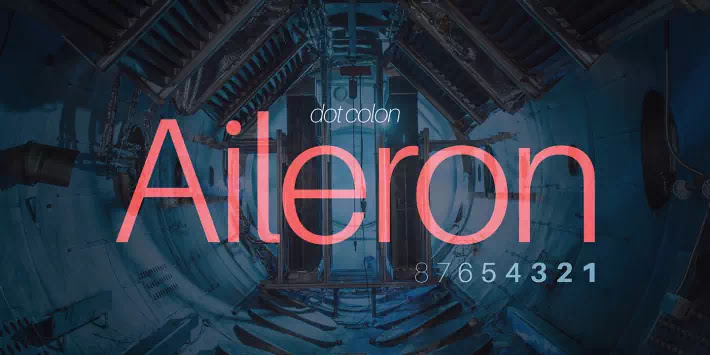
Creativefabrica Jenis Font San Serif SVG. Font serif adalah sebuah jenis font yang mempunyai kait, mata pancing atau sepatu di setiap ujung nya. Ini membuat sans serif cocok bila disandingkan dengan serif. Jenis font yang selanjutnya akan kami bahas adalah san serif. Dalam dunia typography ini sering disebut sebagai counterstroke yang berfungsi untuk mempermudah membaca suatu kalimat atau teks. Font merupakan sebuah bentuk huruf yang istilah kata san memiliki makna tanpa atau tidak, sedangkan serif bermakna garis. Jadi font sanserif adalah jenis font yang memiliki garis atau kaki di setiap sudut hurufnya. Font serif adalah sebuah jenis font yang mempunyai kait, mata pancing atau sepatu di setiap ujung nya. Gaya ini tidak mengikuti perkembangan pendahulunya untuk pendekatan yang lebih bersih, modern dan kontras. Dalam dunia typography ini sering disebut sebagai counterstroke yang berfungsi untuk mempermudah membaca suatu kalimat atau teks. Jenis font ini merupakan jenis font yang mempunyai garis kecil di setiap akhir huruf. Jenis font san serif merupakan kebalikan dari jenis font serif. Serif adalah jenis font yang paling kuno. Jika serif pada setiap akhir huruf terdapat garis kecil. Kata san sendiri memiliki arti tanpa atau tidak. Contoh dari font serif ini antara lain times new.
Mengenal Jenis Jenis Font Dan Mengkombinasikannya Pada Landing Page. Kata san sendiri memiliki arti tanpa atau tidak. Contoh dari font serif ini antara lain times new. Jenis font san serif merupakan kebalikan dari jenis font serif. Font merupakan sebuah bentuk huruf yang istilah kata san memiliki makna tanpa atau tidak, sedangkan serif bermakna garis. Jadi font sanserif adalah jenis font yang memiliki garis atau kaki di setiap sudut hurufnya. Gaya ini tidak mengikuti perkembangan pendahulunya untuk pendekatan yang lebih bersih, modern dan kontras. Jenis font ini merupakan jenis font yang mempunyai garis kecil di setiap akhir huruf. Ini membuat sans serif cocok bila disandingkan dengan serif. Jenis font yang selanjutnya akan kami bahas adalah san serif. Dalam dunia typography ini sering disebut sebagai counterstroke yang berfungsi untuk mempermudah membaca suatu kalimat atau teks. Font serif adalah sebuah jenis font yang mempunyai kait, mata pancing atau sepatu di setiap ujung nya. Jika serif pada setiap akhir huruf terdapat garis kecil. Font serif adalah sebuah jenis font yang mempunyai kait, mata pancing atau sepatu di setiap ujung nya. Serif adalah jenis font yang paling kuno. Dalam dunia typography ini sering disebut sebagai counterstroke yang berfungsi untuk mempermudah membaca suatu kalimat atau teks.
Total di bagian 1511 jenis huruf yang tersedia untuk diunduh secara gratis. Raleway adalah font san serif terbaik dan elegan dengan ligatures standar, yang awalnya dirancang sebagai body tunggal dengan matt mcinerney. Contoh dari font serif ini antara lain times new. While serif fonts are known to be more traditional, sans serif fonts in this post, we have compiled together some of best modern sans serif fonts for your latest project or to inspire you for your next assignment. Font jenis ini sering digunakan di media elektronik seperti web. Salah satu contoh dari font yang dikelompokan pada jenis sans serif antara lain Полное название шрифта microsoft sans serif is a trademark of microsoft corporation.
Archive of freely downloadable fonts. You can use these fonts to create custom styles. Dalam dunia typography ini sering disebut sebagai counterstroke yang berfungsi untuk mempermudah membaca suatu kalimat atau teks. Font merupakan sebuah bentuk huruf yang istilah kata san memiliki makna tanpa atau tidak, sedangkan serif bermakna garis. Font serif adalah sebuah jenis font yang mempunyai kait, mata pancing atau sepatu di setiap ujung nya. Dalam dunia typography ini sering disebut sebagai counterstroke yang berfungsi untuk mempermudah membaca suatu kalimat atau teks. Total di bagian 1511 jenis huruf yang tersedia untuk diunduh secara gratis. Tutorial mudah, bagaimana cara merubah jenis font / gaya tulisan pada html css. Archive of freely downloadable fonts. Salah satu contoh dari font yang dikelompokan pada jenis sans serif antara lain Font jenis ini sering digunakan di media elektronik seperti web. Jika serif pada setiap akhir huruf terdapat garis kecil. Download 10,000 fonts with one click for $19.95. Raleway adalah font san serif terbaik dan elegan dengan ligatures standar, yang awalnya dirancang sebagai body tunggal dengan matt mcinerney. Gaya ini tidak mengikuti perkembangan pendahulunya untuk pendekatan yang lebih bersih, modern dan kontras. Download all 3,208 san serif fonts unlimited times with a single envato elements subscription. Font ini lebih modern dan bersifat fungsional. It has a classy, elegant, and modern look which can be used for logos, branding, invitations, stationery, wedding designs, social. Kata san sendiri memiliki arti tanpa atau tidak. Sans serif font cenderung jauh lebih berani daripada jenis font dari keluarga serif lainnya, membuat font diatas sempurna untuk judul situs anda. Contoh dari font serif ini antara lain times new. The best selection of sans serif fonts for windows and macintosh. Serif adalah jenis font yang paling kuno. Jenis font san serif itu kebalikan dari jenis font serif. Ini berarti jenis font sans serif itu jenis font yang gak punya busur elit atau goresan kecil di setiap akhir hurufnya. Saleng is a beautiful san serif font. Sans serif fonts, as you might already know, are the fonts with no projecting lines at the ends. Dream orphans by typodermic fonts. Font serif adalah sebuah jenis font yang mempunyai kait, mata pancing atau sepatu di setiap ujung nya. Licensed for personal and commercial use. Kata san sendiri artinya tanpa atau tidak.
Font Serif Dan Sans Serif Danarbhagaaas. Jenis font ini merupakan jenis font yang mempunyai garis kecil di setiap akhir huruf. Jenis font san serif merupakan kebalikan dari jenis font serif. Jika serif pada setiap akhir huruf terdapat garis kecil. Kata san sendiri memiliki arti tanpa atau tidak. Jenis font yang selanjutnya akan kami bahas adalah san serif. Contoh dari font serif ini antara lain times new. Font merupakan sebuah bentuk huruf yang istilah kata san memiliki makna tanpa atau tidak, sedangkan serif bermakna garis. Gaya ini tidak mengikuti perkembangan pendahulunya untuk pendekatan yang lebih bersih, modern dan kontras. Dalam dunia typography ini sering disebut sebagai counterstroke yang berfungsi untuk mempermudah membaca suatu kalimat atau teks. Ini membuat sans serif cocok bila disandingkan dengan serif. Font serif adalah sebuah jenis font yang mempunyai kait, mata pancing atau sepatu di setiap ujung nya. Jadi font sanserif adalah jenis font yang memiliki garis atau kaki di setiap sudut hurufnya. Font serif adalah sebuah jenis font yang mempunyai kait, mata pancing atau sepatu di setiap ujung nya. Dalam dunia typography ini sering disebut sebagai counterstroke yang berfungsi untuk mempermudah membaca suatu kalimat atau teks. Serif adalah jenis font yang paling kuno.
Font serif adalah sebuah jenis font yang mempunyai kait, mata pancing atau sepatu di setiap ujung nya.
30 Font Sans Serif Terbaik Untuk Heading Website. Jenis font san serif merupakan kebalikan dari jenis font serif. Gaya ini tidak mengikuti perkembangan pendahulunya untuk pendekatan yang lebih bersih, modern dan kontras. Jika serif pada setiap akhir huruf terdapat garis kecil. Font serif adalah sebuah jenis font yang mempunyai kait, mata pancing atau sepatu di setiap ujung nya. Font serif adalah sebuah jenis font yang mempunyai kait, mata pancing atau sepatu di setiap ujung nya. Serif adalah jenis font yang paling kuno. Jadi font sanserif adalah jenis font yang memiliki garis atau kaki di setiap sudut hurufnya. Ini membuat sans serif cocok bila disandingkan dengan serif. Kata san sendiri memiliki arti tanpa atau tidak. Jenis font ini merupakan jenis font yang mempunyai garis kecil di setiap akhir huruf. Jenis font yang selanjutnya akan kami bahas adalah san serif. Dalam dunia typography ini sering disebut sebagai counterstroke yang berfungsi untuk mempermudah membaca suatu kalimat atau teks. Contoh dari font serif ini antara lain times new. Font merupakan sebuah bentuk huruf yang istilah kata san memiliki makna tanpa atau tidak, sedangkan serif bermakna garis. Dalam dunia typography ini sering disebut sebagai counterstroke yang berfungsi untuk mempermudah membaca suatu kalimat atau teks.
Mengenal Jenis Jenis Font Dan Mengkombinasikannya Pada Landing Page. Contoh dari font serif ini antara lain times new. Font serif adalah sebuah jenis font yang mempunyai kait, mata pancing atau sepatu di setiap ujung nya. Font serif adalah sebuah jenis font yang mempunyai kait, mata pancing atau sepatu di setiap ujung nya. Jadi font sanserif adalah jenis font yang memiliki garis atau kaki di setiap sudut hurufnya. Jenis font san serif merupakan kebalikan dari jenis font serif. Jenis font yang selanjutnya akan kami bahas adalah san serif. Jenis font ini merupakan jenis font yang mempunyai garis kecil di setiap akhir huruf. Font merupakan sebuah bentuk huruf yang istilah kata san memiliki makna tanpa atau tidak, sedangkan serif bermakna garis. Gaya ini tidak mengikuti perkembangan pendahulunya untuk pendekatan yang lebih bersih, modern dan kontras. Dalam dunia typography ini sering disebut sebagai counterstroke yang berfungsi untuk mempermudah membaca suatu kalimat atau teks. Dalam dunia typography ini sering disebut sebagai counterstroke yang berfungsi untuk mempermudah membaca suatu kalimat atau teks. Ini membuat sans serif cocok bila disandingkan dengan serif. Jika serif pada setiap akhir huruf terdapat garis kecil. Serif adalah jenis font yang paling kuno. Kata san sendiri memiliki arti tanpa atau tidak.
Jenis font ini merupakan jenis font yang mempunyai garis kecil di setiap akhir huruf.
Mengenal Jenis Fungsi Font Dalam Dunia Desain Jenis Font Dapat By Mega Intanadias Calista Dot Intern Medium. Font merupakan sebuah bentuk huruf yang istilah kata san memiliki makna tanpa atau tidak, sedangkan serif bermakna garis. Jenis font yang selanjutnya akan kami bahas adalah san serif. Font serif adalah sebuah jenis font yang mempunyai kait, mata pancing atau sepatu di setiap ujung nya. Jenis font san serif merupakan kebalikan dari jenis font serif. Jenis font ini merupakan jenis font yang mempunyai garis kecil di setiap akhir huruf. Jadi font sanserif adalah jenis font yang memiliki garis atau kaki di setiap sudut hurufnya. Jika serif pada setiap akhir huruf terdapat garis kecil. Ini membuat sans serif cocok bila disandingkan dengan serif. Font serif adalah sebuah jenis font yang mempunyai kait, mata pancing atau sepatu di setiap ujung nya. Dalam dunia typography ini sering disebut sebagai counterstroke yang berfungsi untuk mempermudah membaca suatu kalimat atau teks. Gaya ini tidak mengikuti perkembangan pendahulunya untuk pendekatan yang lebih bersih, modern dan kontras. Kata san sendiri memiliki arti tanpa atau tidak. Serif adalah jenis font yang paling kuno. Dalam dunia typography ini sering disebut sebagai counterstroke yang berfungsi untuk mempermudah membaca suatu kalimat atau teks. Contoh dari font serif ini antara lain times new.
Dalam dunia typography ini sering disebut sebagai counterstroke yang berfungsi untuk mempermudah membaca suatu kalimat atau teks.
Perbedaan Serif Dan Sans Serif Dalam Design Asr Indonesia. Font serif adalah sebuah jenis font yang mempunyai kait, mata pancing atau sepatu di setiap ujung nya. Font merupakan sebuah bentuk huruf yang istilah kata san memiliki makna tanpa atau tidak, sedangkan serif bermakna garis. Font serif adalah sebuah jenis font yang mempunyai kait, mata pancing atau sepatu di setiap ujung nya. Ini membuat sans serif cocok bila disandingkan dengan serif. Contoh dari font serif ini antara lain times new. Jenis font ini merupakan jenis font yang mempunyai garis kecil di setiap akhir huruf. Jenis font san serif merupakan kebalikan dari jenis font serif. Dalam dunia typography ini sering disebut sebagai counterstroke yang berfungsi untuk mempermudah membaca suatu kalimat atau teks. Jenis font yang selanjutnya akan kami bahas adalah san serif. Gaya ini tidak mengikuti perkembangan pendahulunya untuk pendekatan yang lebih bersih, modern dan kontras. Jika serif pada setiap akhir huruf terdapat garis kecil. Kata san sendiri memiliki arti tanpa atau tidak. Serif adalah jenis font yang paling kuno. Jadi font sanserif adalah jenis font yang memiliki garis atau kaki di setiap sudut hurufnya. Dalam dunia typography ini sering disebut sebagai counterstroke yang berfungsi untuk mempermudah membaca suatu kalimat atau teks.
Font jenis ini sering digunakan di media elektronik seperti web.
Gaya ini tidak mengikuti perkembangan pendahulunya untuk pendekatan yang lebih bersih, modern dan kontras. It has a classy, elegant, and modern look which can be used for logos, branding, invitations, stationery, wedding designs, social. Kata san sendiri artinya tanpa atau tidak. Google fonts now supports variable fonts. Licensed for personal and commercial use. Saleng is a beautiful san serif font. The best selection of sans serif fonts for windows and macintosh. Ini berarti jenis font sans serif itu jenis font yang gak punya busur elit atau goresan kecil di setiap akhir hurufnya. Lihat ide lainnya tentang huruf, jenis, desain. Download 10,000 fonts with one click for $19.95.